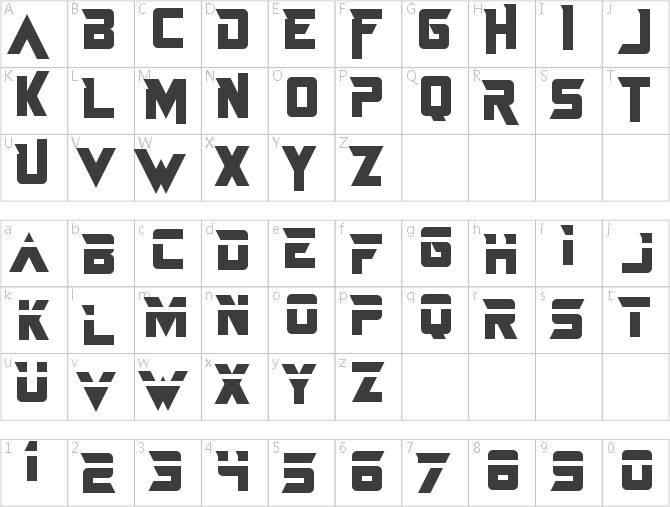
字體名稱: Just-In
Just-In-The-Firestorm-Regular
Just-In-The-Firestorm-Regular字體字庫是一款讓人賞心悅目、百看不厭的英文字體,適合各類廣告和產品包裝設計應用,字體大小0.02MB,格式為ttf字體,上傳用戶是我,Dirac,作者/版權方為未知